お祭りのポスターや縁日の看板には、会場のにぎわいが伝わる文字が似合います。力強い筆文字で伝統的に見せる方法もあれば、丸いフォントで家族向けの楽しさを出す方法もあります。出店や催しの内容に合わせて選んでみましょう。
今回はフォントラボから、お祭り・縁日の制作物に使いたい日本語フリーフォントを15個紹介します。大きく見せる祭り名や出店名と、日時・料金・会場案内に向くフォントを分けて選びました。遠くから読む看板は、装飾だけでなく文字の大きさと背景との明暗差も確認してください。
看板と案内に合わせて選ぶお祭り・縁日向け日本語フリーフォント
藍原江戸文字
| おすすめの場面 | かなのお祭り名/江戸風の表題/短い出店名 |
江戸情緒のあるフォントで、祭りの入口を飾る。
「藍原江戸文字」は、千社文字を参考にした、太く密度のある形が特徴のフォントです。江戸風のポスターや短い出店名に使うと、伝統的なにぎわいを表現できます。フリー版の漢字は小学校2年生までが中心で、「祭」など使えない文字もあるため、かなの「まつり」で試すのがおすすめ。英字や算用数字は別のフォントで補い、商標登録の制限にも注意しましょう。
玉ねぎ楷書「激」
| おすすめの場面 | 祭りのタイトル/演目の見出し/屋台の看板 |
力強い筆文字フォントで、祭りの熱気を。
「玉ねぎ楷書「激」」は、大胆なハネやハライに勢いがある筆文字フォントです。祭りのタイトルや演目の見出しを大きく見せたいときにおすすめ。無料版でもJIS第一水準漢字を含みますが、地域名や固有の演目名は入力して確認しましょう。情報用のフォントとは分け、タイトルの周りに余白を残すと、筆の動きが窮屈にならず伝わります。
衡山毛筆フォント
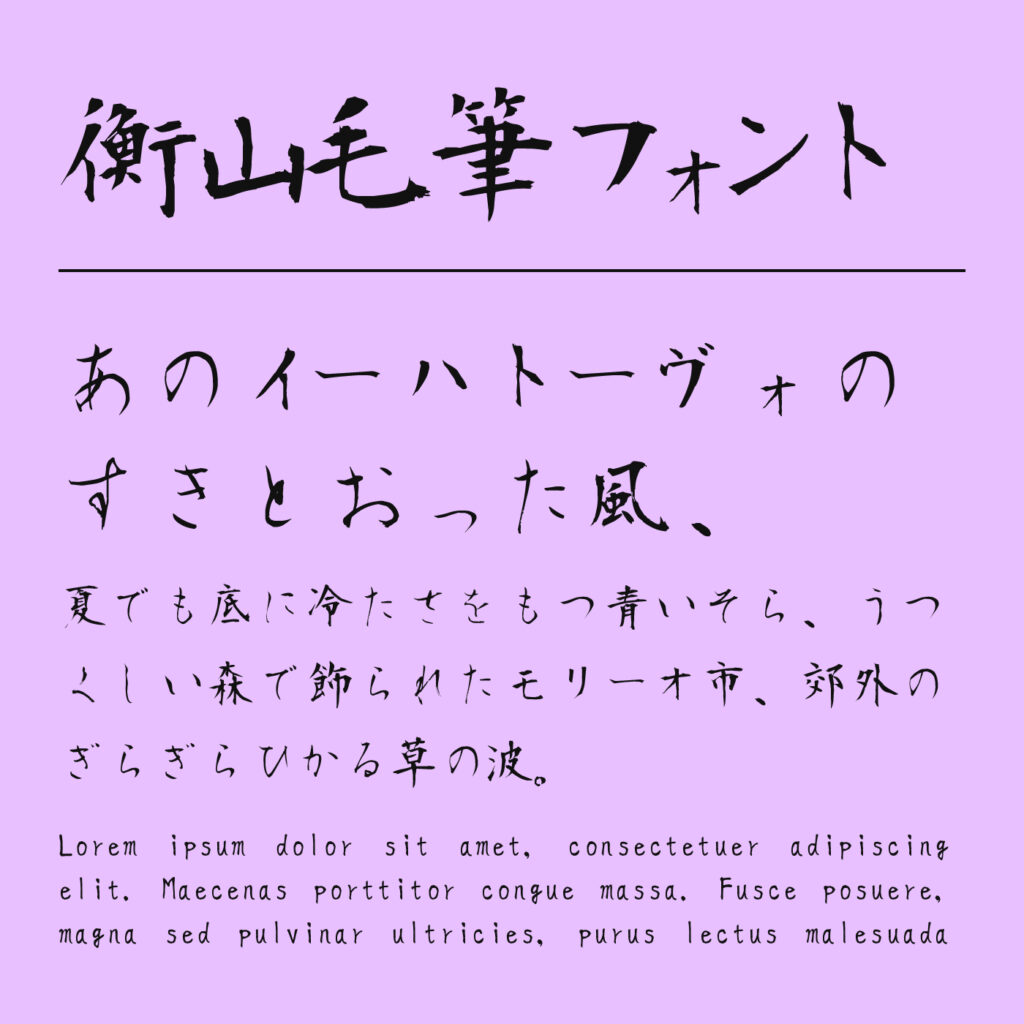
| おすすめの場面 | 伝統行事の表題/催しの紹介/和風の案内状 |
筆の流れが美しいフォントで、伝統的な表情に。
「衡山毛筆フォント」は、筆圧の変化やハネ、ハライが感じられる毛筆フォントです。伝統行事の表題や催しの案内を、力強さだけでなく落ち着きもある印象にしたいときに向いています。看板では細部が見える大きさを確保し、筆文字の流れを楽しむのがおすすめ。日時やアクセスには別のフォントを使い、読む人が迷わない案内に整えましょう。
筆ごしらえ
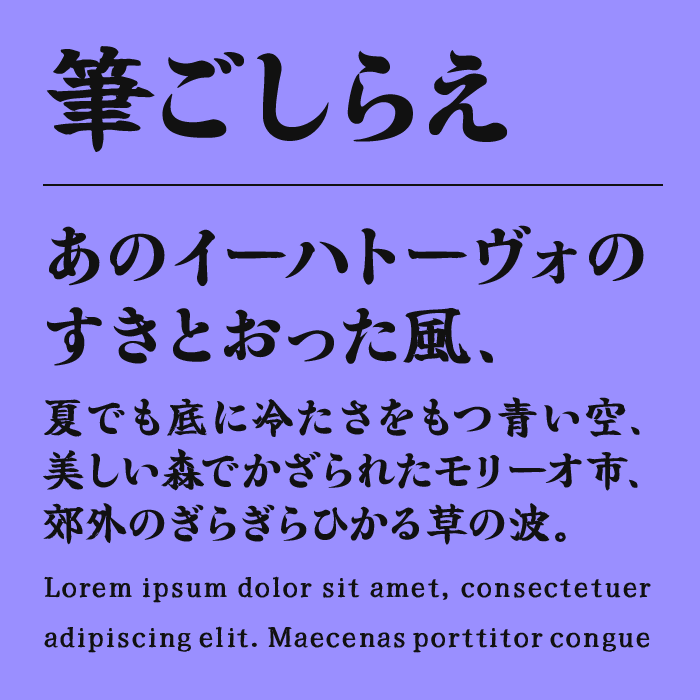
| おすすめの場面 | お祭りの大きな見出し/屋台の紹介/告知画像 |
太い筆文字フォントで、目を引く表題に。
「筆ごしらえ」は、太い線の存在感がある筆文字フォントです。お祭りの告知画像や屋台紹介で、短い表題を大きく見せる使い方におすすめ。配布元には字形の誤りが含まれる可能性についての注意があるため、使う文字を確認してください。日時や金額を伝えるフォントとしては選ばず、装飾的な見出しと情報欄を分けて取り入れましょう。
ささふでフォント
| おすすめの場面 | 屋台のメニュー見出し/出店紹介/短い挨拶 |
さらりとした筆のフォントで、人のいる店先に。
「ささふでフォント」は、素早く書いたような筆ペンの表情があるフォントです。屋台のメニュー見出しや出店者からの短い挨拶で、人の温度を感じる案内を作れます。格式のある毛筆フォントより、気軽な店先の雰囲気に寄せたいときにおすすめ。価格の数字は読み取りやすい文字で揃え、筆文字は商品名やひと言に使うと整理しやすくなります。
佑字 肅(Yuji Syuku)
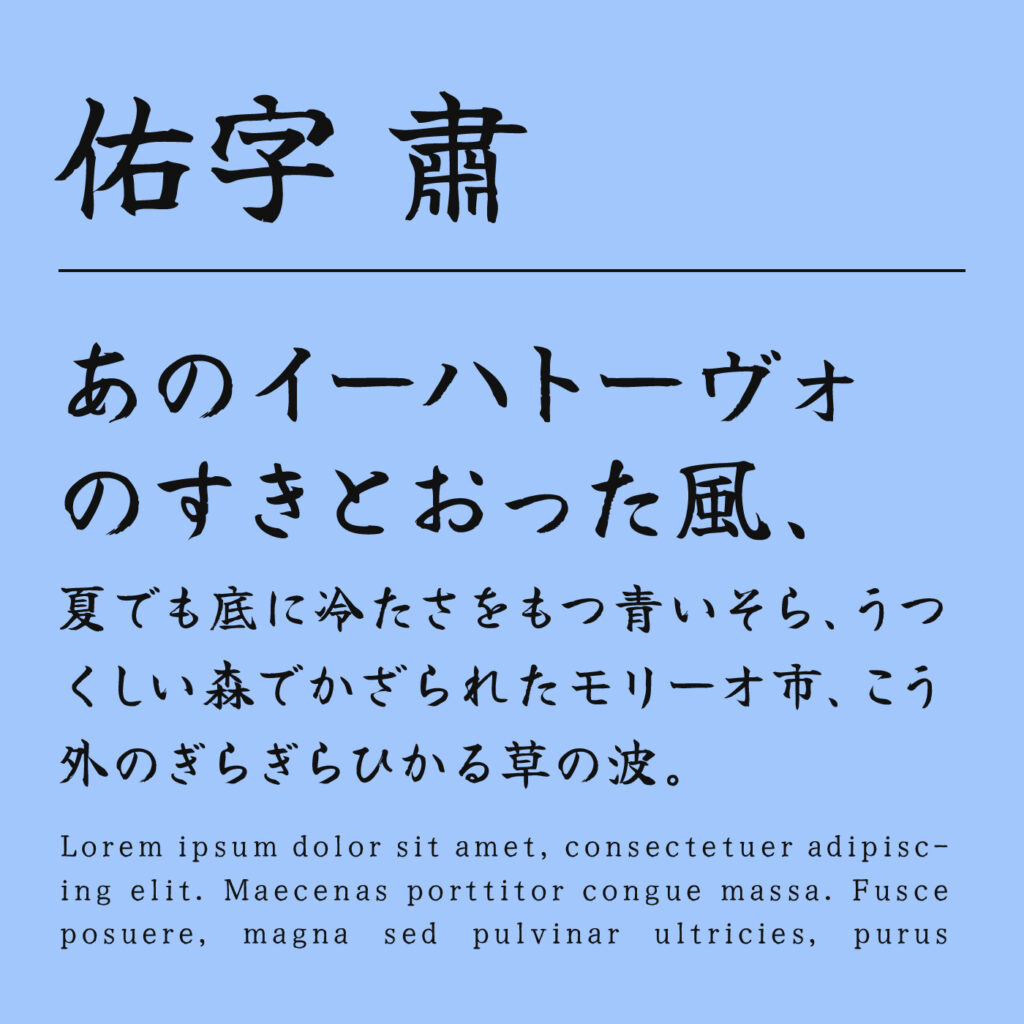
| おすすめの場面 | 地域行事の案内/和の演目/落ち着いた出店カード |
整った筆文字フォントで、催しを丁寧に紹介。
「佑字 肅(Yuji Syuku)」は、明朝を基盤にした筆の形が、整った印象を作るフォントです。地域行事の紹介や和の演目など、勢い一辺倒ではなく丁寧に案内したい部分に向いています。大きな祭り名は太いフォント、演目の紹介はこのフォントという使い分けもおすすめ。短い文章をゆったり組むと、筆の細かな表情を保ちながら読みやすく見せられます。
佑字 朴(Yuji Boku)
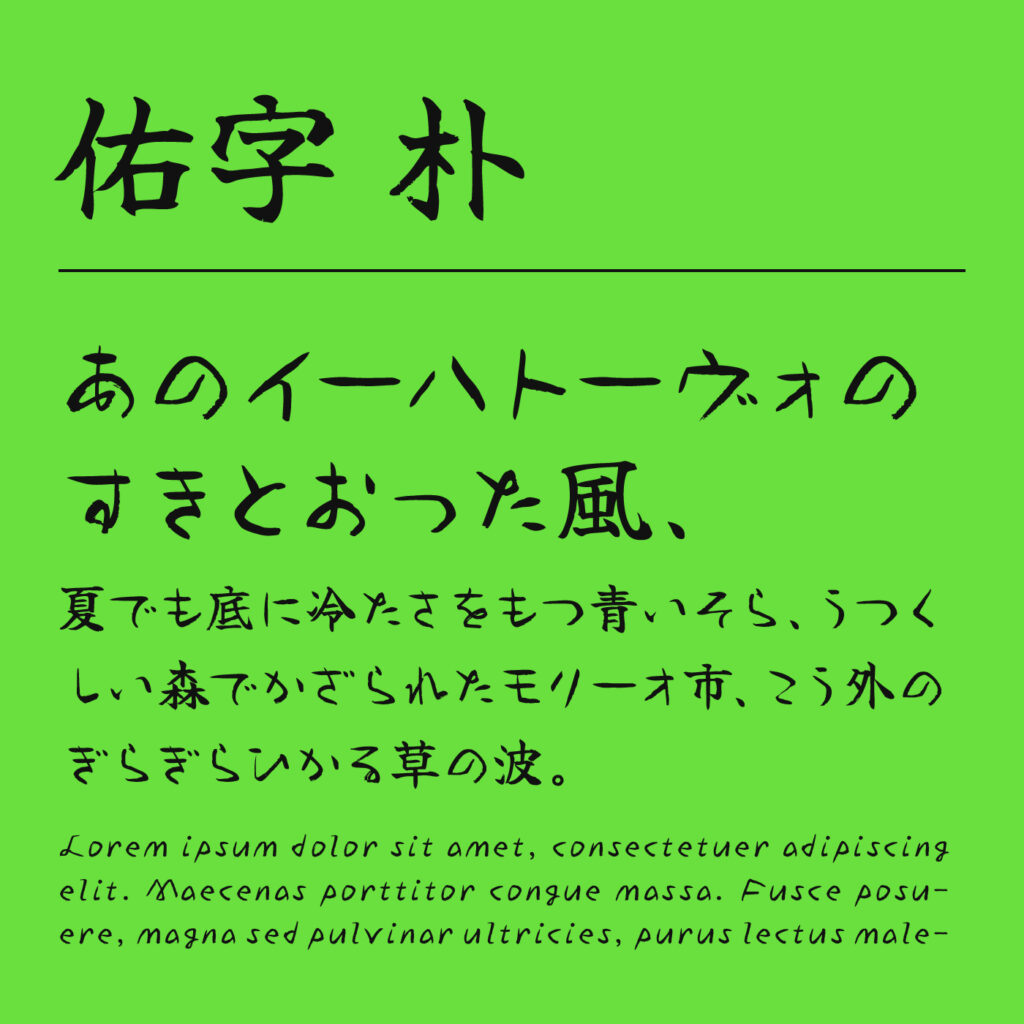
| おすすめの場面 | 屋台や出店の名前/和風の看板/催しの表題 |
かすれのある筆文字フォントで、素朴なにぎわいに。
「佑字 朴(Yuji Boku)」は、筆のかすれと力強い漢字、柔らかなかなの組み合わせが魅力のフォントです。屋台の名前や和風の看板に、手で書いたような素朴さを加えたいときにおすすめ。整いすぎたゴシックフォントとは違う、人の気配が出せます。英字は独特な形になるので、英語も使う看板では読みやすさを見ながら組み合わせを決めましょう。
しょかきさらり
| おすすめの場面 | 夕涼みの表題/季節の挨拶/和風イベントの一言 |
流れる筆のフォントで、涼やかな余白を。
「しょかきさらり」は、さらりと流れる筆致が特徴のフォントです。夕涼みの催しや季節の挨拶など、祭りの熱気とは違う軽やかさを表現したいときに向いています。崩した字形もあるため、遠くから読む案内より短い装飾コピーにおすすめ。商標登録や文字の形自体を主な価値とする商品の販売には制限があるので、グッズ用途のフォント選びでは規約を確認しましょう。
デラまるゴシック
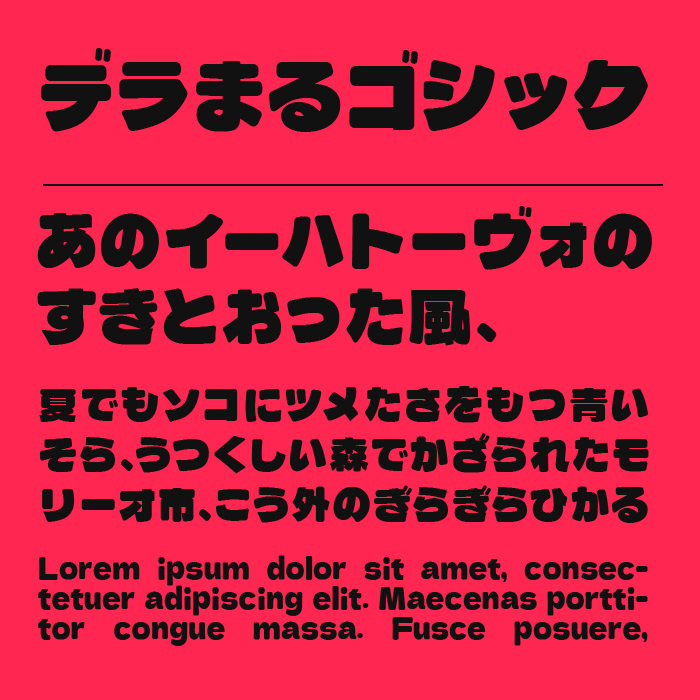
| おすすめの場面 | 家族向け縁日/遊びのコーナー名/参加募集 |
丸く太いフォントで、楽しさを大きく見せる。
「デラまるゴシック」は、極太の線と丸い輪郭を合わせたゴシックフォントです。家族向けの縁日や遊びのコーナー名を、元気で入りやすい印象にしたいときにおすすめ。筆文字フォントとは違うポップさがあり、イラストのある告知にも合わせやすい候補です。ルール説明は細めの文字にし、看板の中で遊びの名前が最初に見える構成にしましょう。
カラメルホップ
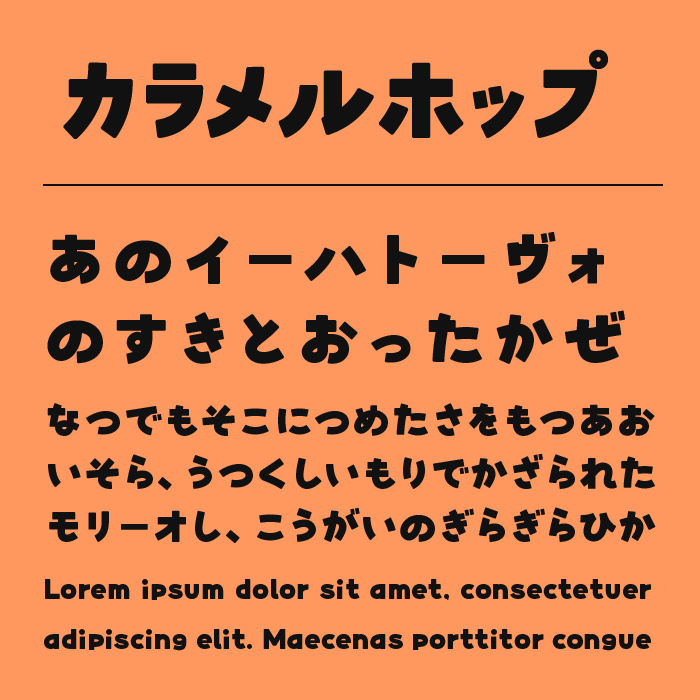
| おすすめの場面 | かなの遊び名/子ども向け看板/短い呼びかけ |
弾むフォントで、縁日のわくわく感を。
「カラメルホップ」は、太いかなが跳ねるように並ぶ、楽しい印象のフォントです。子ども向けの遊び名や短い呼びかけを大きく見せる場面に向いています。漢字は収録されていないので、かなで表せる名前を選ぶのがおすすめ。料金や受付時間は落ち着いたフォントで添えると、楽しさを前面に出しながら、利用に必要な情報も読みやすく伝えられます。
くらむぼんフォント
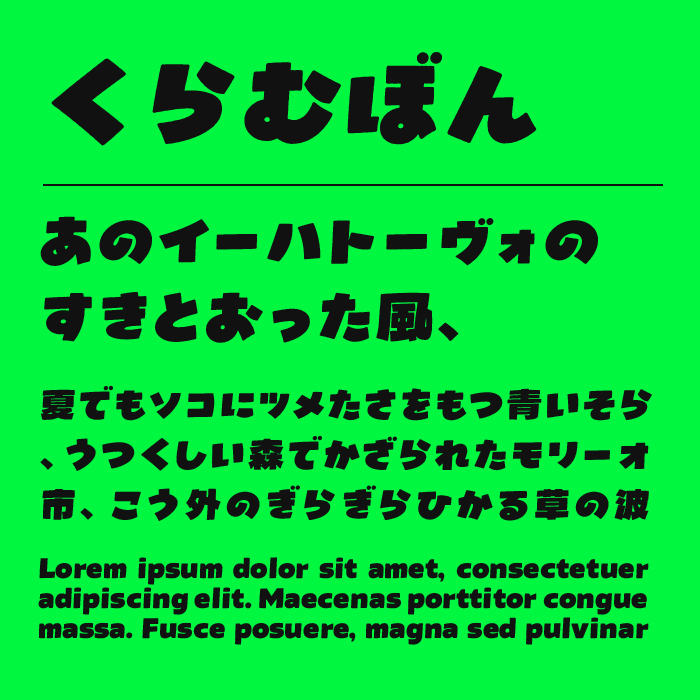
| おすすめの場面 | にぎやかな出店名/地域イベント/催しの見出し |
ふっくらしたフォントで、賑やかな看板に。
「くらむぼんフォント」は、太く膨らみのある形と少し不均一な輪郭が特徴のフォントです。地域のイベントや出店の名前に、手作り感を残した元気な表情を加えられます。筆文字フォントほど和の印象を強めず、幅広い遊びや企画に合わせたいときにおすすめ。文字を飾りで囲みすぎず、輪郭がわかる余白を取って看板の主役にしましょう。
なぎの
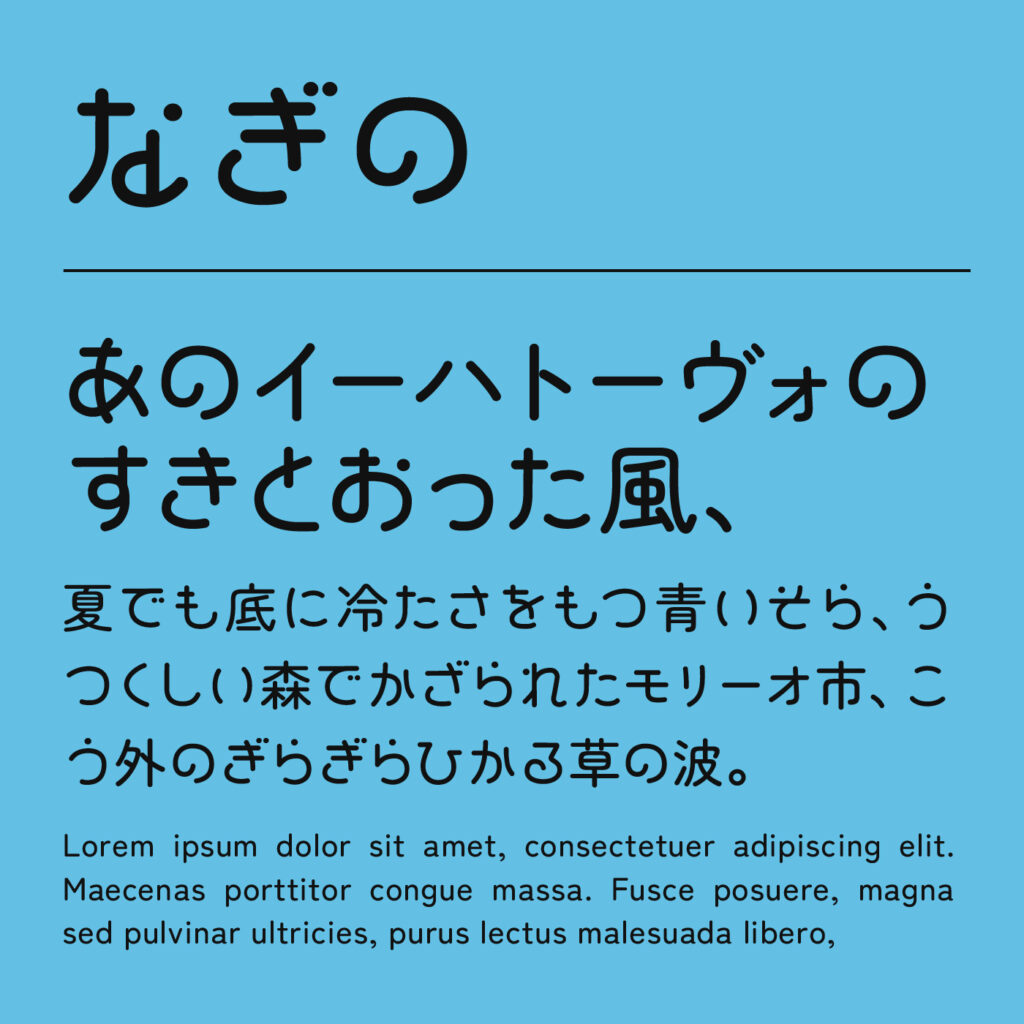
| おすすめの場面 | 海辺の縁日/夏の催し/かな中心の表題 |
海を感じるかなのフォントで、夏らしい個性を。
「なぎの」は、海や船、窓を思わせるモチーフを取り入れたかなが特徴のフォントです。海辺の縁日や夏の催しで、会場らしい表情を付けたいときにおすすめ。すべての文字が装飾されるわけではないため、企画名を入力して形を確認しましょう。案内フォントとは役割を分け、短い表題の中で海のモチーフを楽しむ使い方が向いています。
シロフクG
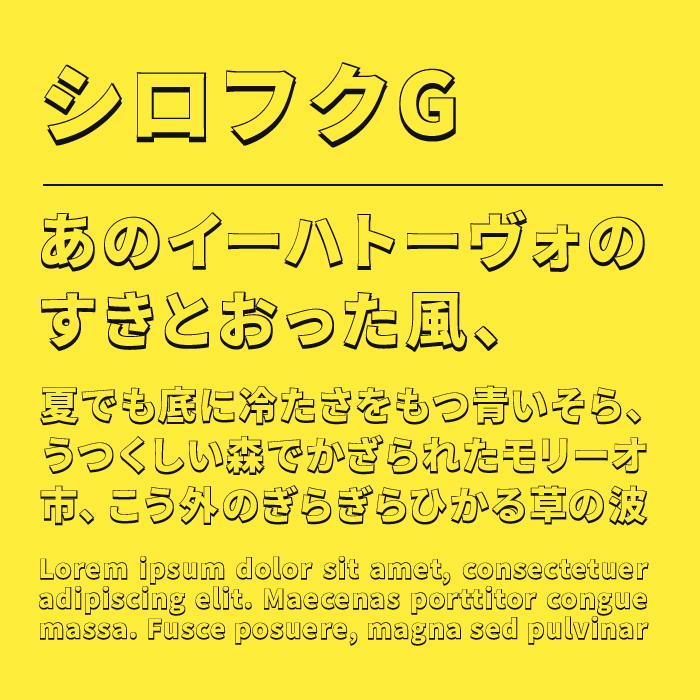
| おすすめの場面 | 縁日のポスター/遊びの看板/参加企画名 |
輪郭と影のフォントで、立体的な楽しさを。
「シロフクG」は、袋文字に影を付けたような立体感があるフォントです。縁日のポスターや遊びの看板に、ポップな装飾を加えたいときに向いています。フォント自体に線が多いので、複雑な写真より無地の背景に置く方が形が伝わります。金額やルールまで同じ文字にせず、企画名だけを大きく見せると、にぎやかでも整理された案内になります。
いろはマル
| おすすめの場面 | 地域のお祭り案内/会場マップの見出し/休憩所の表示 |
懐かしさのあるフォントで、やさしい地域の案内に。
「いろはマル」は、丸い輪郭と古風なかなの線が、親しみのある印象を作るフォントです。地域のお祭りの案内や会場マップで、硬くなりすぎずに情報を見せたいときにおすすめ。筆文字のタイトルフォントと合わせても、案内部分を穏やかにまとめられます。地図の細かなラベルは文字サイズを十分に取り、目印と重ならない位置へ配置しましょう。
LINE Seed JP
| おすすめの場面 | 日時と会場/料金表/参加方法や注意事項 |
素直なフォントで、来場者が迷わない案内に。
「LINE Seed JP」は、整った形と親しみやすさを持つ日本語フォントです。日時、会場、料金、参加方法など、正確に読んでほしい情報に向いています。祭り名を筆文字やポップなフォントで飾った場合にも、案内欄を落ち着いて支えられます。屋外の掲示は離れた位置からも確認し、文字の大きさと背景との明暗差を優先して調整しましょう。